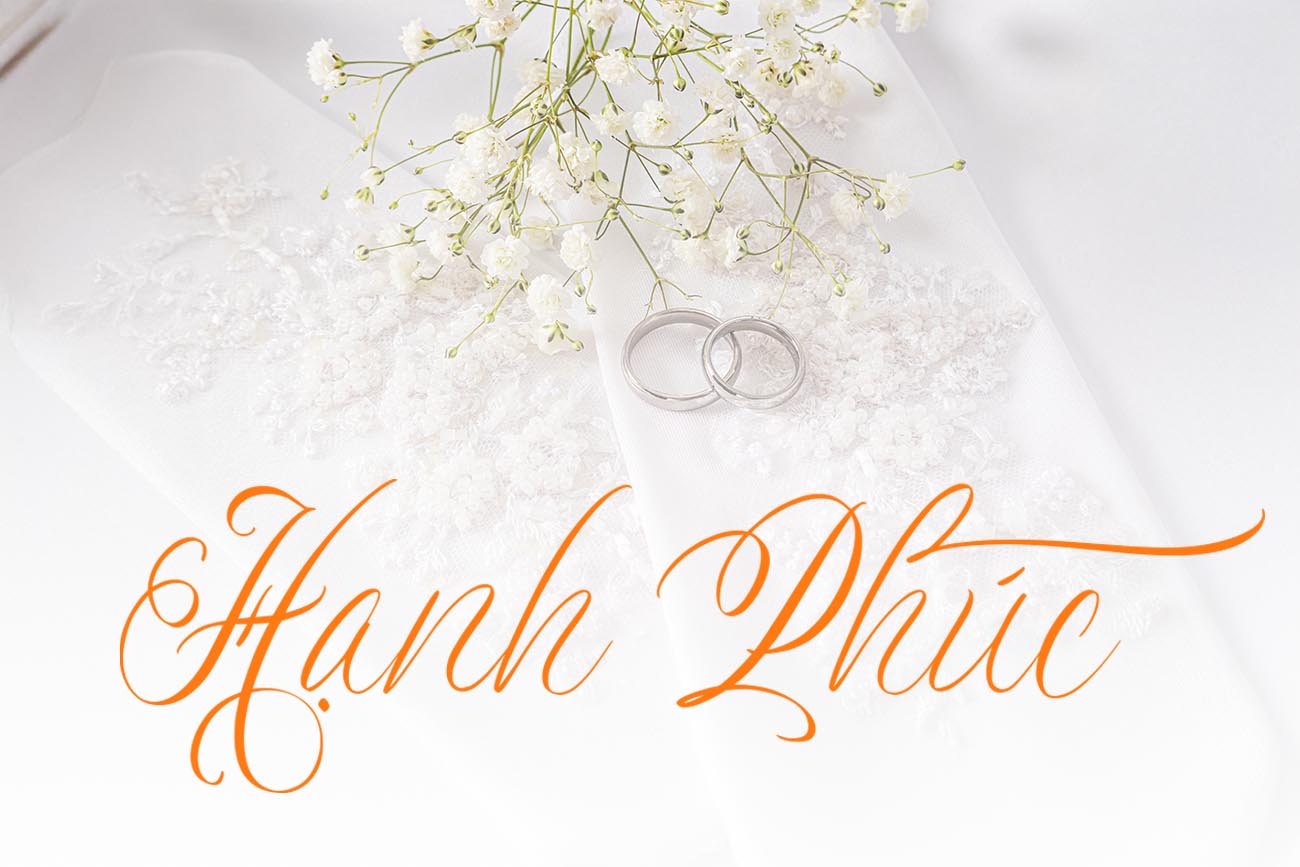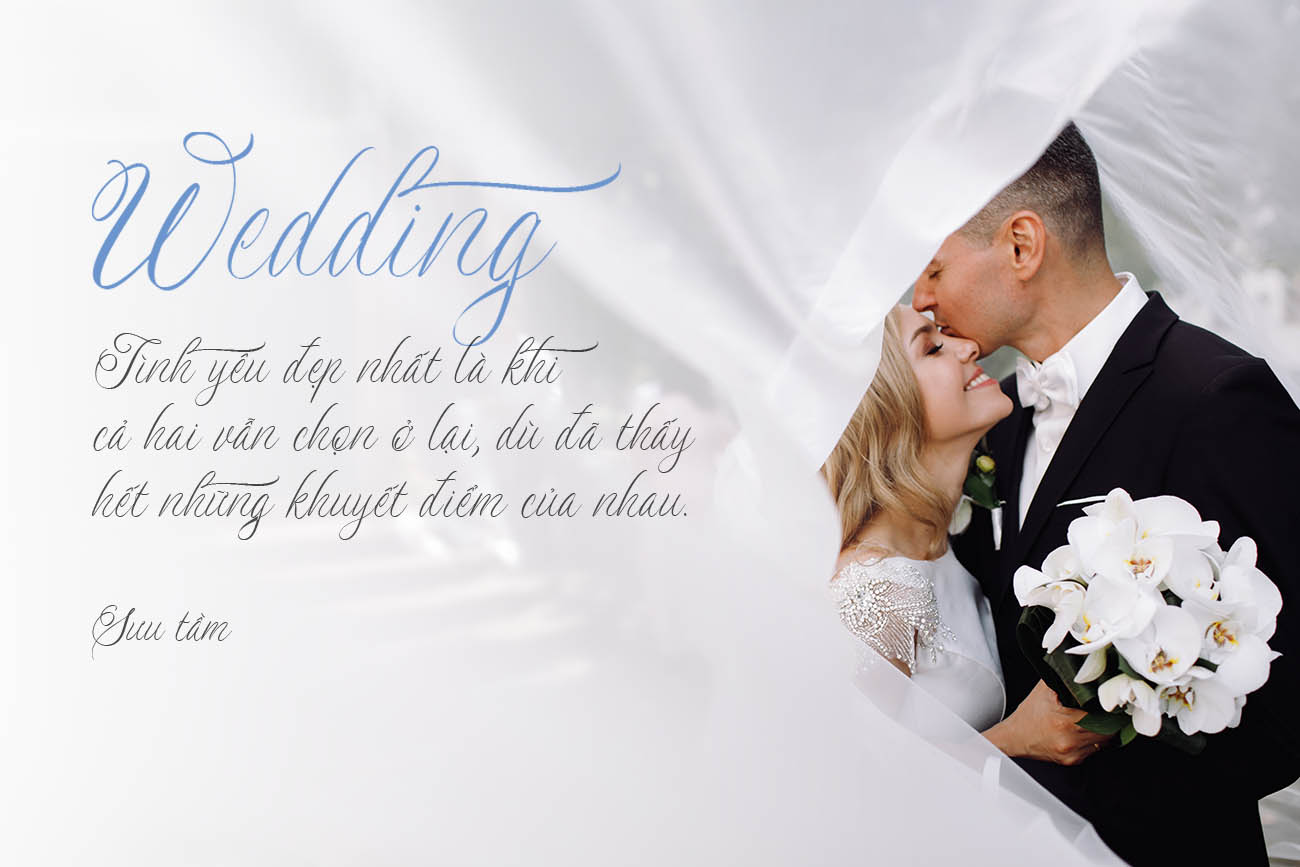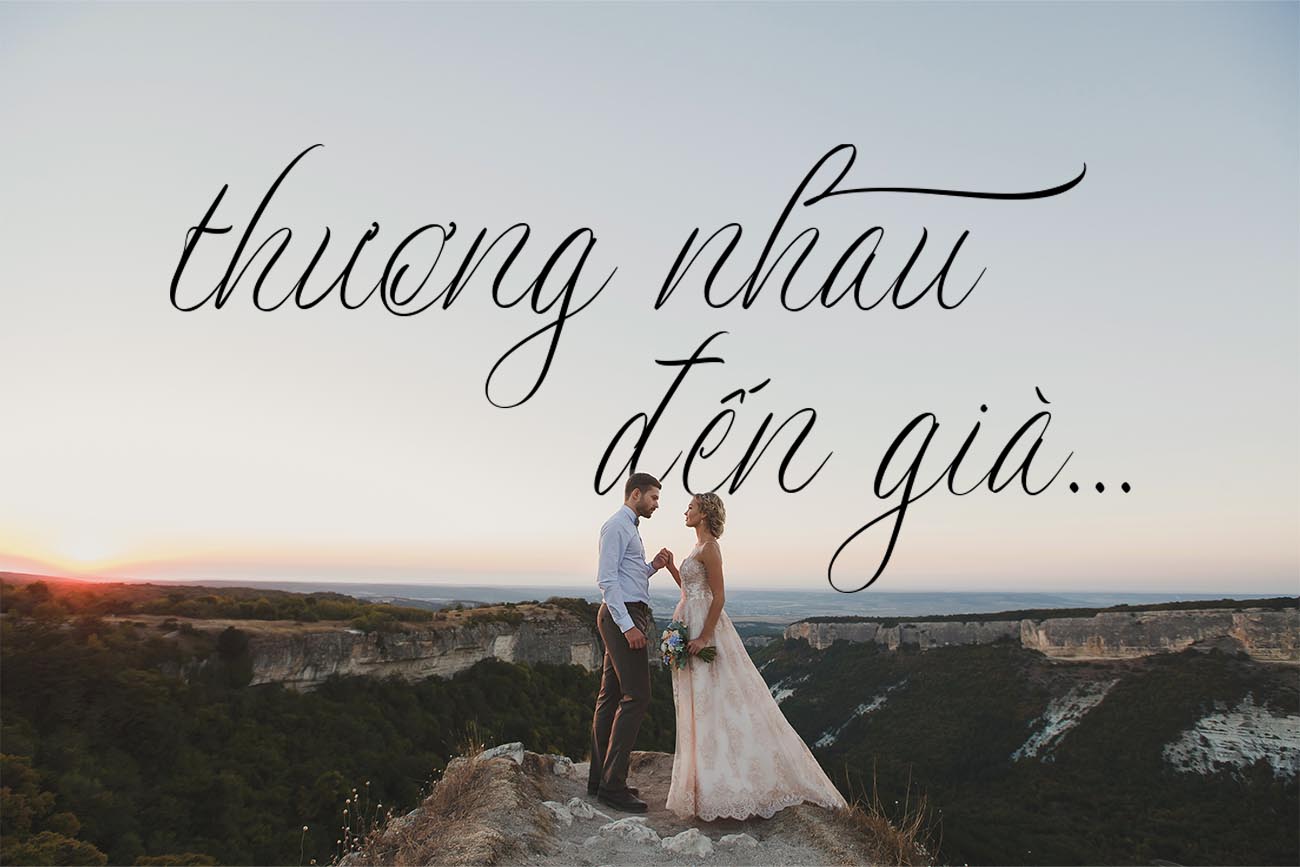
Font chữ đám cưới TH Newly Bridal Việt hóa cho mùa yêu thương
Trong lĩnh vực thiết kế đồ họa, đặc biệt là thiết kế ấn phẩm cho ngày trọng đại, việc lựa chọn Typography phù hợp đóng vai trò quyết định đến cảm xúc của toàn bộ tác phẩm. Hôm nay, chúng tôi xin giới thiệu đến cộng đồng Designer bộ phông chữ TH Newly Bridal, phiên bản Việt hóa hoàn chỉnh từ tác phẩm gốc Newly Bridal của tác giả AZe Type 86.
Vẻ đẹp tinh tế của nét chữ viết tay
TH Newly Bridal không chỉ đơn thuần là một công cụ hiển thị văn bản, mà còn là một tác phẩm nghệ thuật thư pháp kỹ thuật số. Mang đặc trưng của dòng font chữ viết tay hiện đại, bộ phông này sở hữu những đường nét thanh mảnh, tự nhiên nhưng không kém phần phóng khoáng.
Điểm nhấn tạo nên sức hút của TH Newly Bridal chính là sự kết hợp hài hòa giữa các ký tự. Đây là một font chữ uốn lượn đầy nghệ thuật, với các nét nối (ligatures) mềm mại, tạo cảm giác như chữ được viết trực tiếp bằng mực tàu trên giấy lụa. Sự uyển chuyển này giúp thiết kế trở nên sống động, xóa bỏ sự cứng nhắc thường thấy của các phông chữ máy tính thông thường.
Lựa chọn hàng đầu cho các ấn phẩm Wedding
Đúng như tên gọi gốc trên Envato Elements, đây là một font wedding chuẩn mực dành cho các nhà thiết kế chuyên nghiệp. Với phong cách sang trọng và lãng mạn, TH Newly Bridal cực kỳ phù hợp để làm font chữ đám cưới cho các hạng mục như: thiệp mời, thiệp báo hỷ (Save the Date), menu tiệc cưới, bảng tên cô dâu chú rể hay các video phóng sự cưới.
Ngoài ra, tính ứng dụng của font chữ cưới này còn mở rộng sang các lĩnh vực branding, thiết kế logo cho studio áo cưới, tiệm hoa, hoặc các ấn phẩm thời trang cao cấp cần sự bay bổng và tinh tế.
Bản Việt hóa chất lượng từ Fontdep.vn
Mặc dù bản gốc Newly Bridal rất đẹp, nhưng việc thiếu hỗ trợ tiếng Việt có dấu là rào cản lớn đối với các Designer trong nước. Hiểu được điều đó, đội ngũ Fontdep.vn đã thực hiện Việt hóa chi tiết bộ phông này thành phiên bản TH Newly Bridal.
Quá trình Việt hóa được thực hiện tỉ mỉ, đảm bảo các dấu câu được cân chỉnh vị trí hài hòa, không làm phá vỡ cấu trúc của dòng font chữ uốn lượn vốn có. Các ký tự mở rộng và ký tự thay thế (alternates) cũng được giữ nguyên vẹn, giúp Designer thỏa sức sáng tạo mà không lo lỗi font.
Nếu bạn đang tìm kiếm một font chữ viết tay mang đậm hơi thở lãng mạn để tô điểm cho các dự án mùa cưới năm nay, TH Newly Bridal chắc chắn là một cái tên không thể bỏ qua trong thư viện font của bạn. Hãy trải nghiệm ngay sự mượt mà và đẳng cấp mà bộ font này mang lại cho các thiết kế của mình.